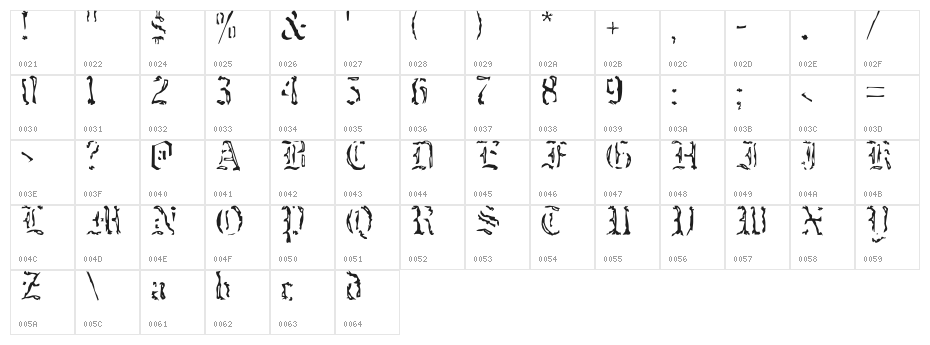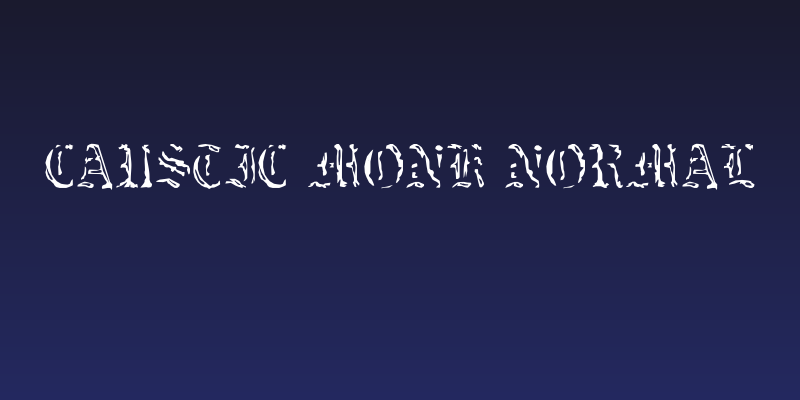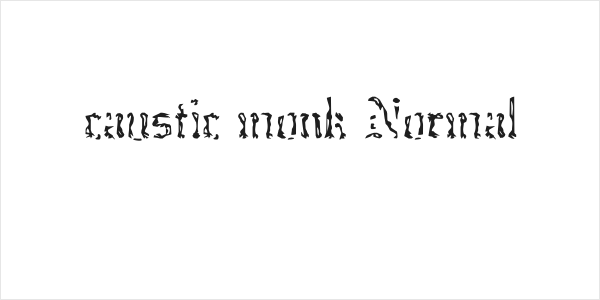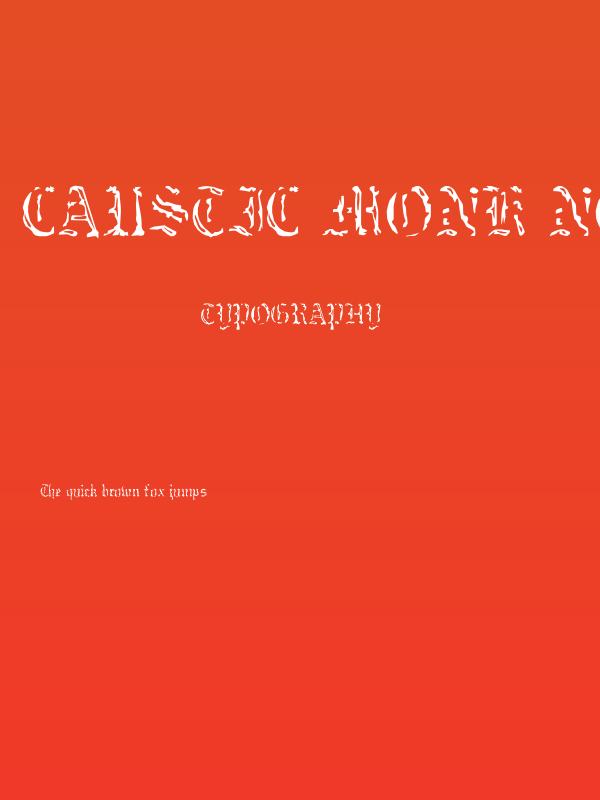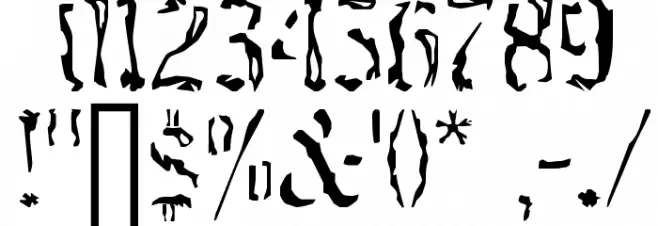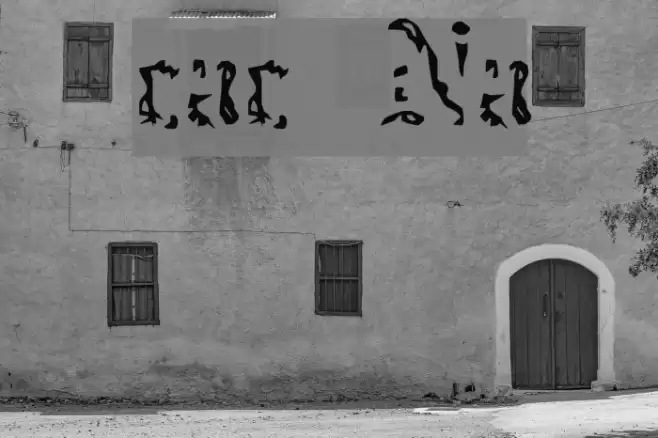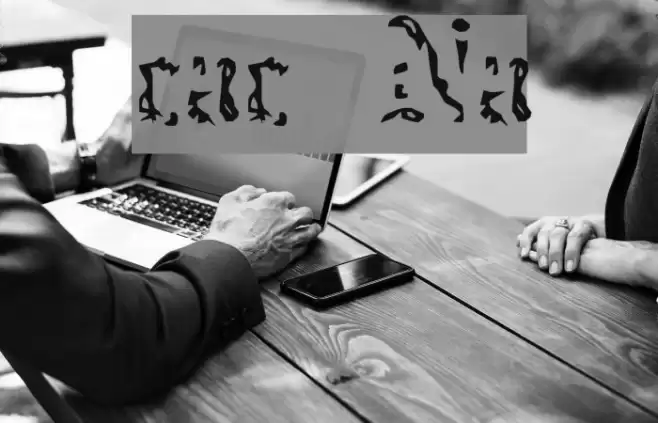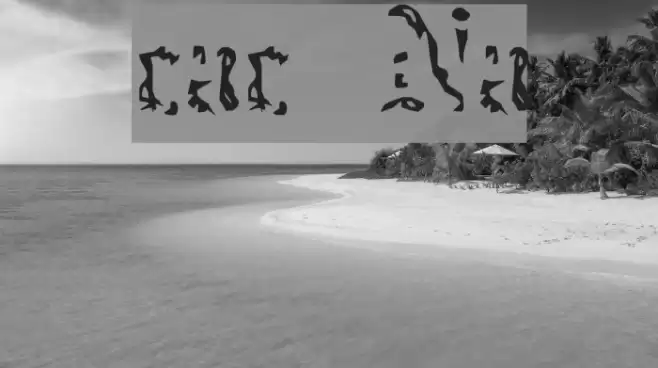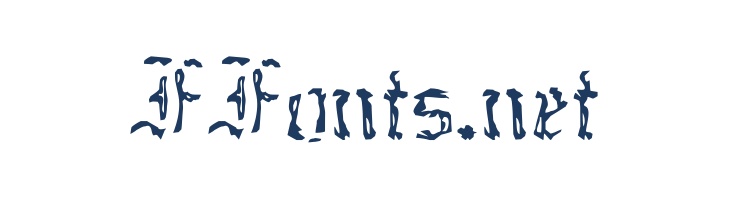
caustic monk Normal Font
| Anwendungsfall | Logos, Headlines, Posters |
| Vorgeschlagene Projekte | Ideal for fantasy-themed posters, book covers, or branding that requires a medieval or gothic touch. |